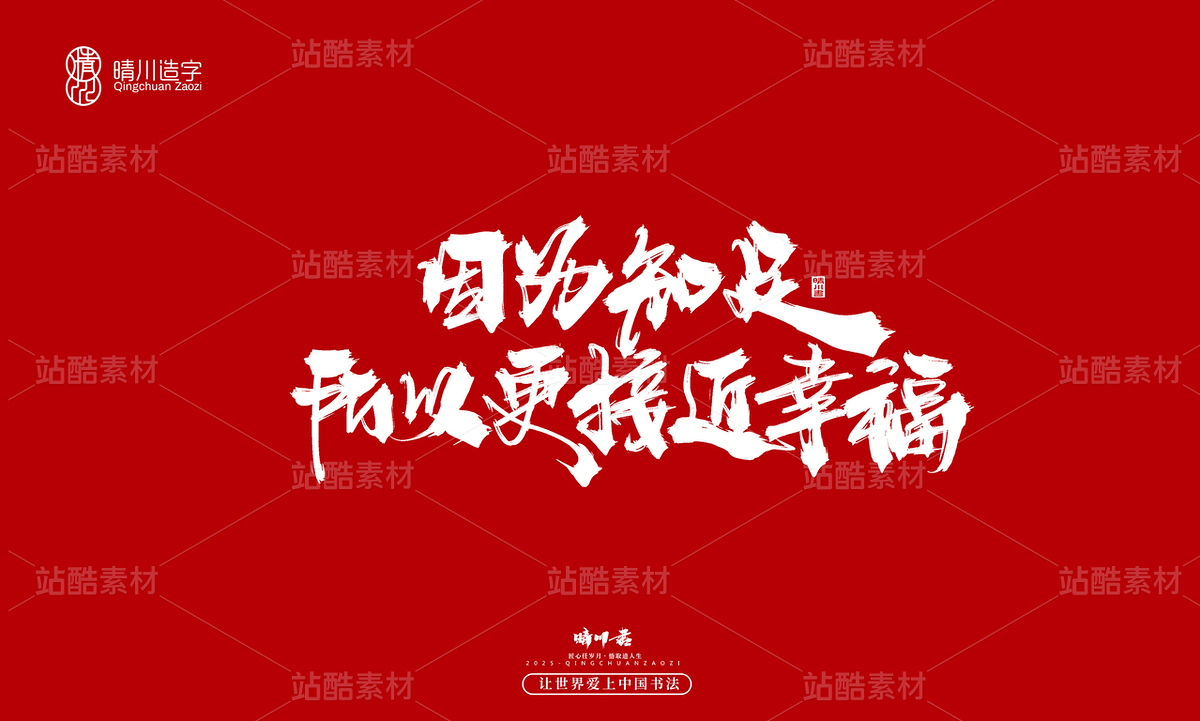
本组素材是中文纯手写体原创素材
因为知足·所以更接近幸福
全套书写共86份,这是其中1份。
本组书写字体,可应用于海报、宣传页、画册、主KV、单页等宣传物料,也可应用于手机壁纸、手机壳、冰箱贴、红包、手提袋、马克杯、鼠标垫、抱枕、卫衣等多种文创产品上。
商业手写书法师-孟晴川
因为知足·所以更接近幸福
全套书写共86份,这是其中1份。
本组书写字体,可应用于海报、宣传页、画册、主KV、单页等宣传物料,也可应用于手机壁纸、手机壳、冰箱贴、红包、手提袋、马克杯、鼠标垫、抱枕、卫衣等多种文创产品上。
商业手写书法师-孟晴川